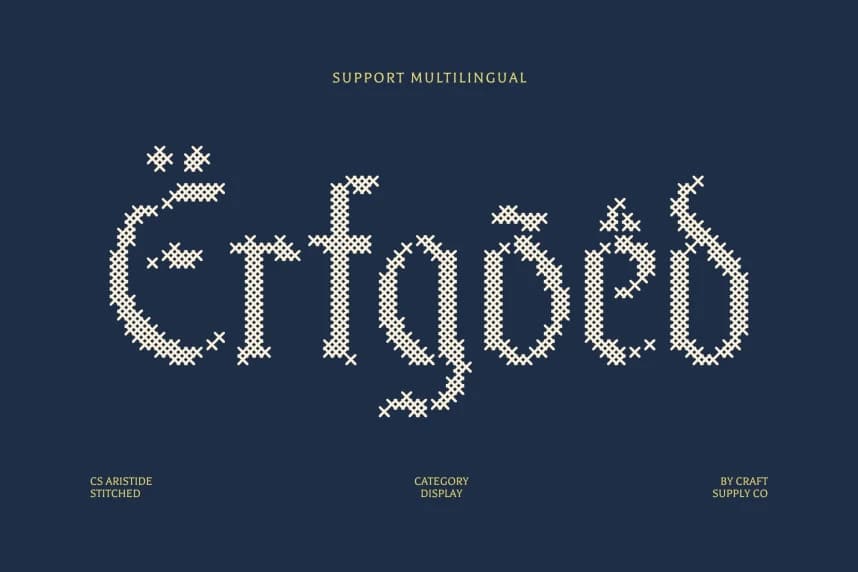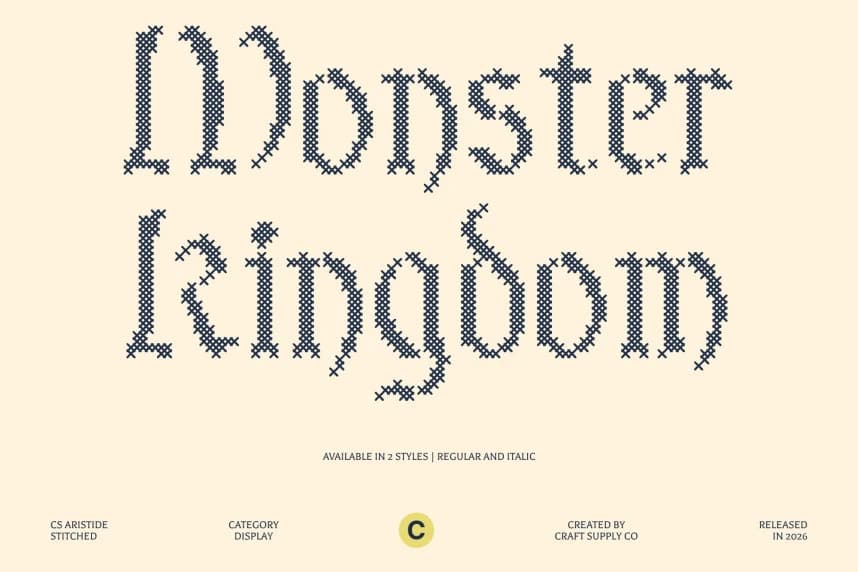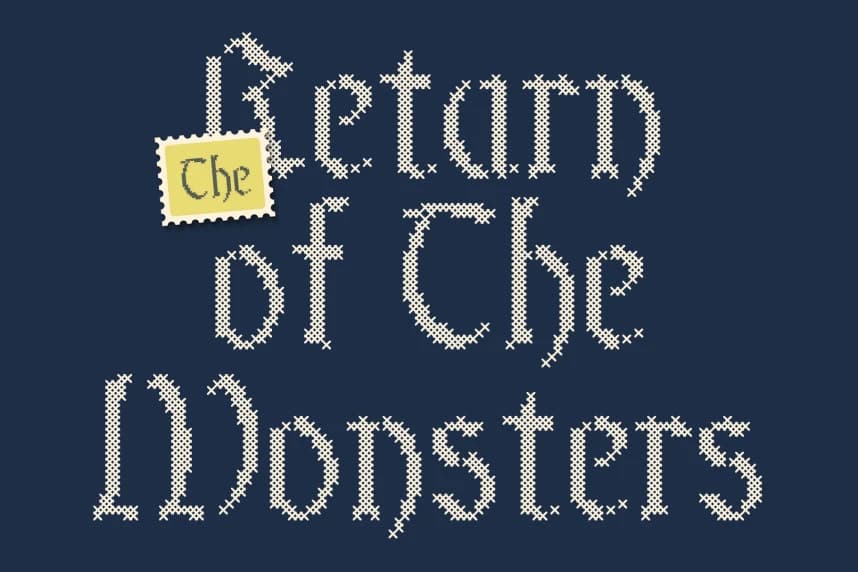
CS Aristide Stitched Yazı Tipi
CS Aristide Stitched Font – Blackletter Font with Modern Gothic Flair Modern Blackletter with Handcrafted Character. Bu, gotik kaligrafinin vahşi ruhunu çağdaş minimalistlikle birleştiren cesur bir Blackletter gösterim yazı tipidir.
CS Aristide Stitched Font – Blackletter Font ile Modern Gotik Tarzı Modern Blackletter ile El Yapımı Karakter. Bu, Gotik kaligrafisinin sert ruhunu çağdaş minimalistlikle birleştiren cesur bir Blackletter gösterim fontudur.